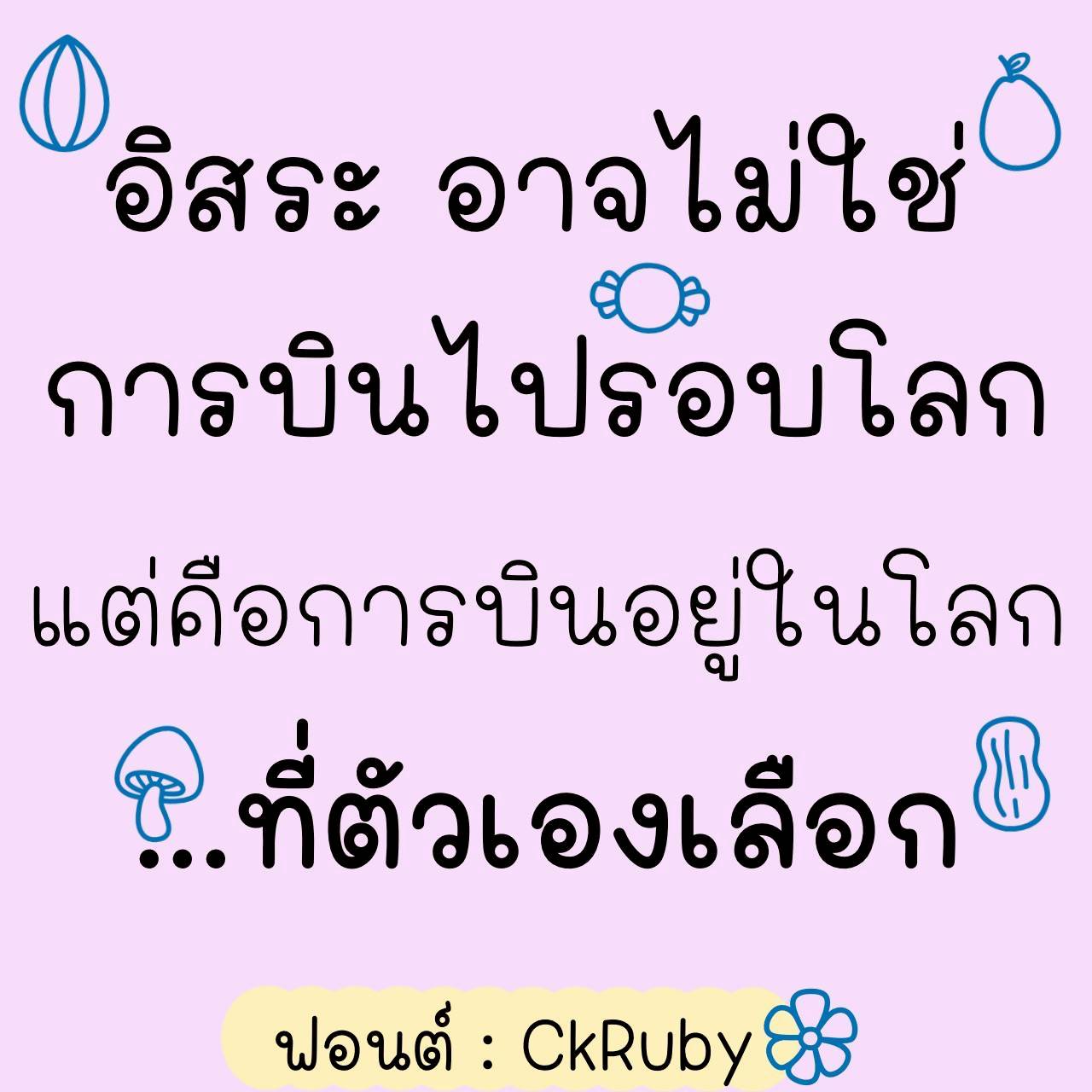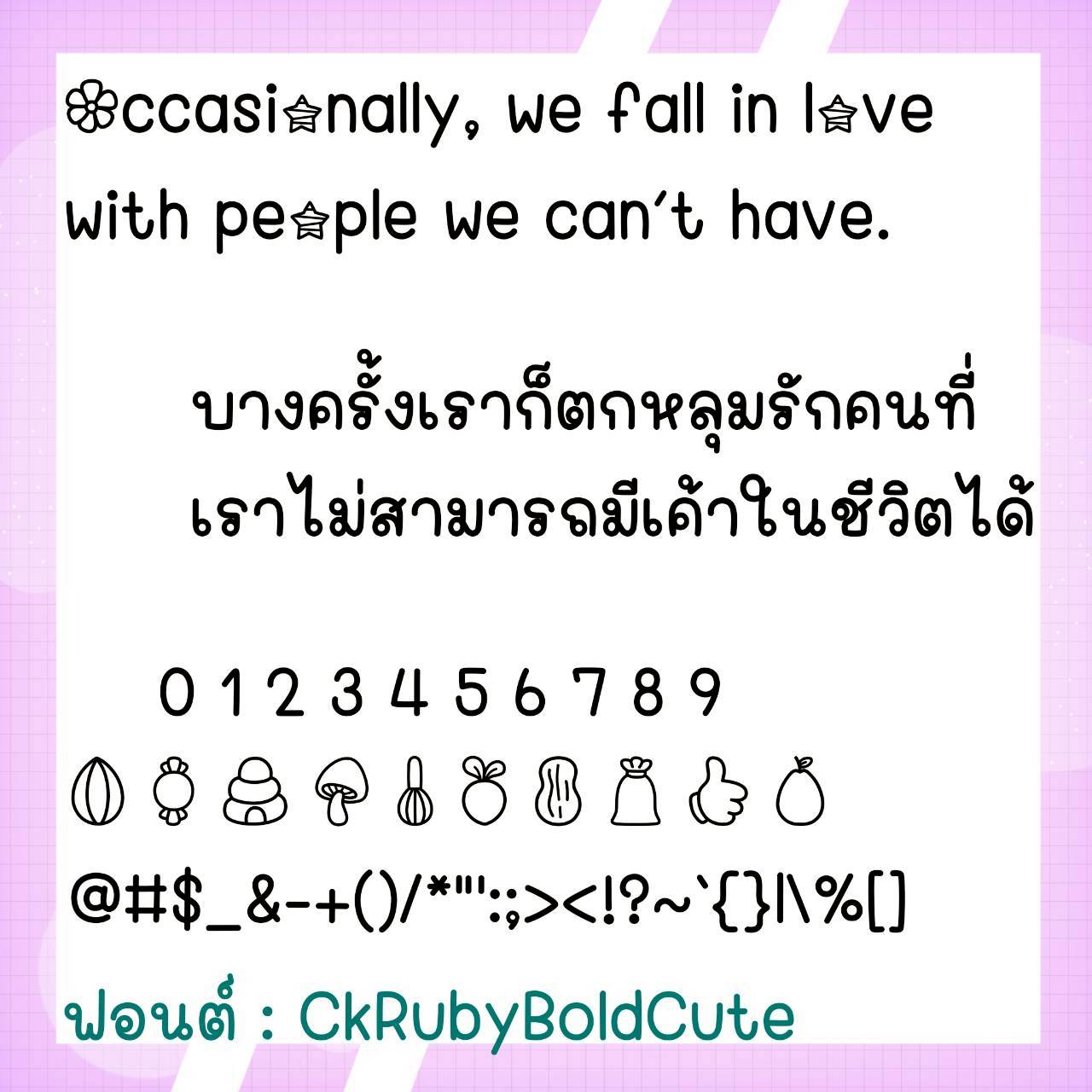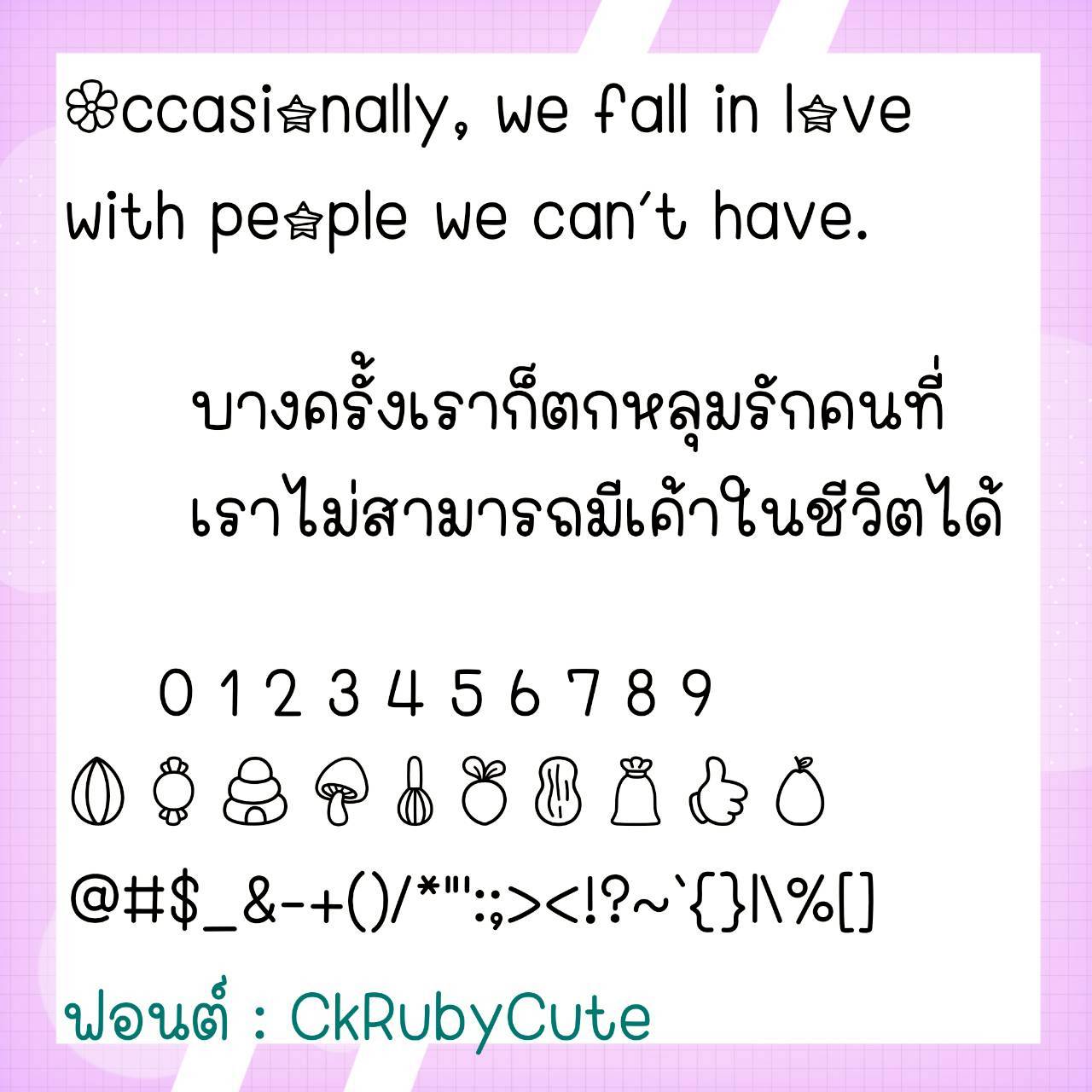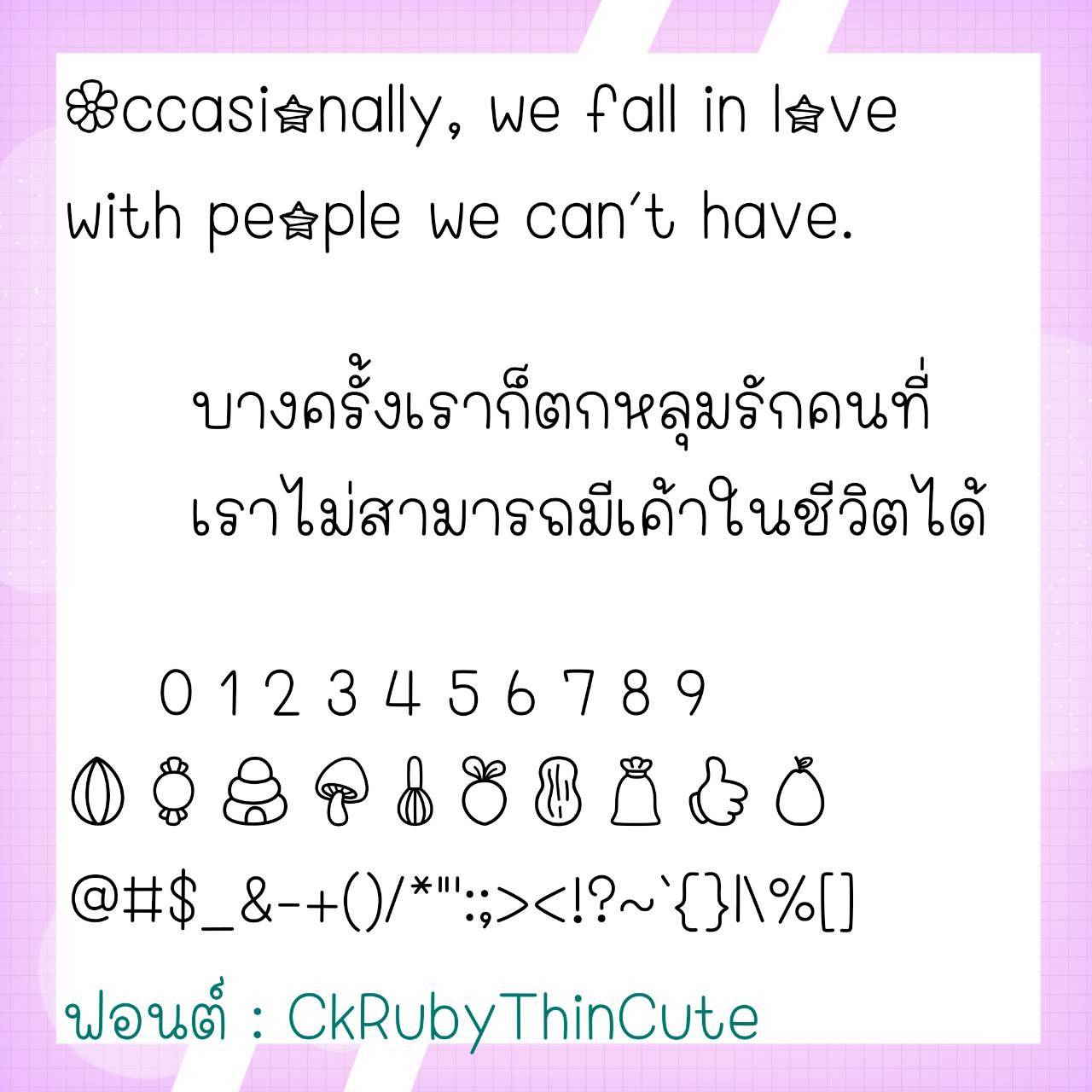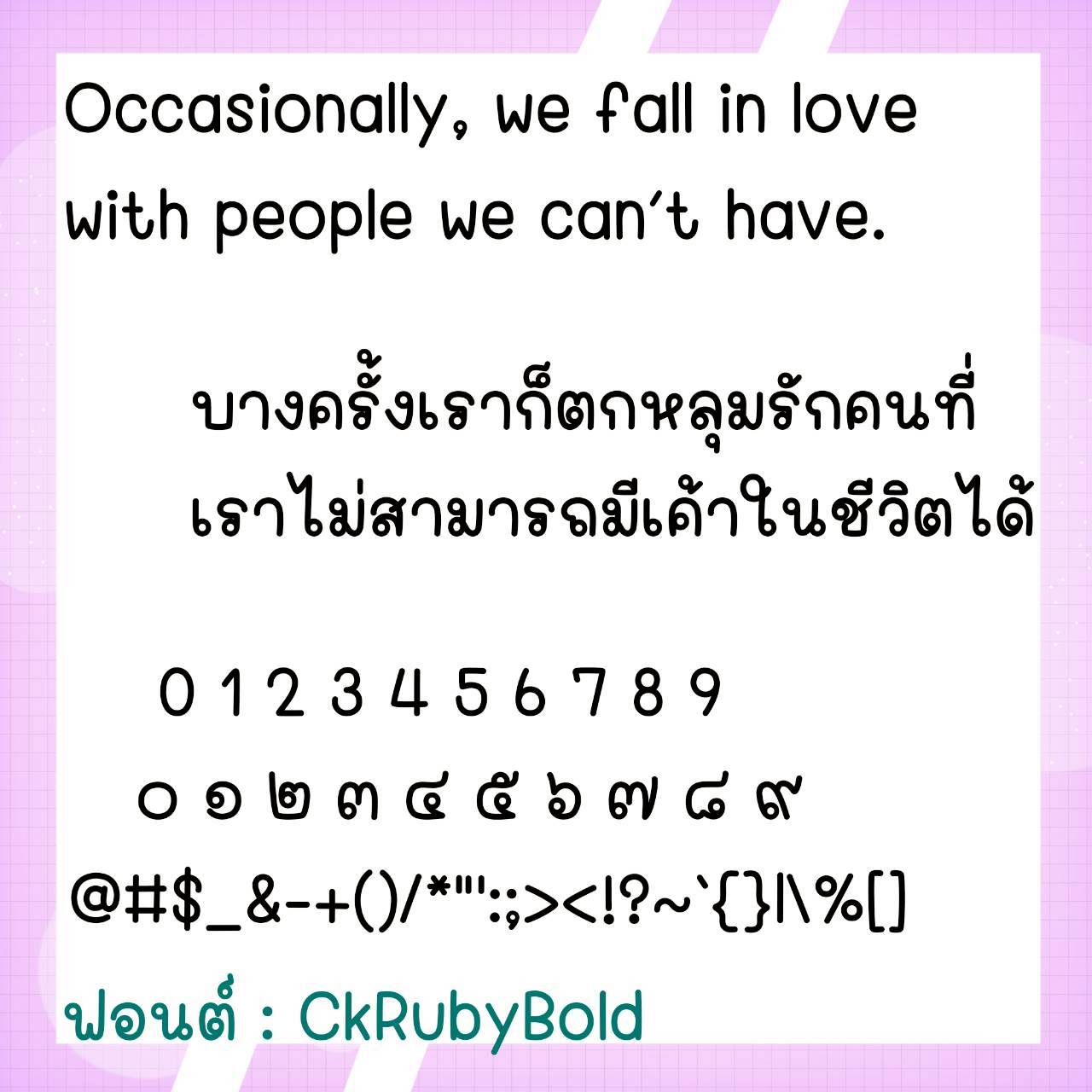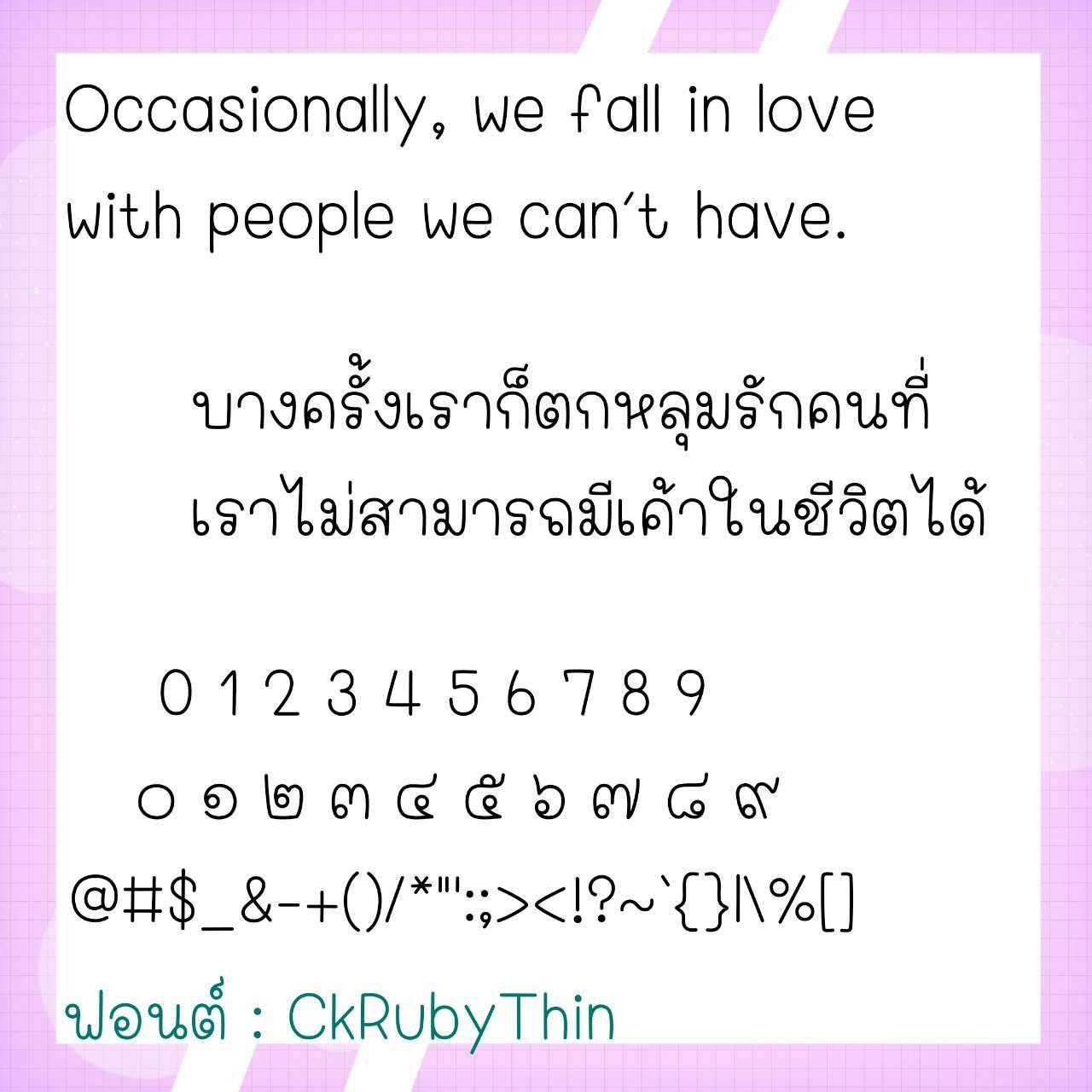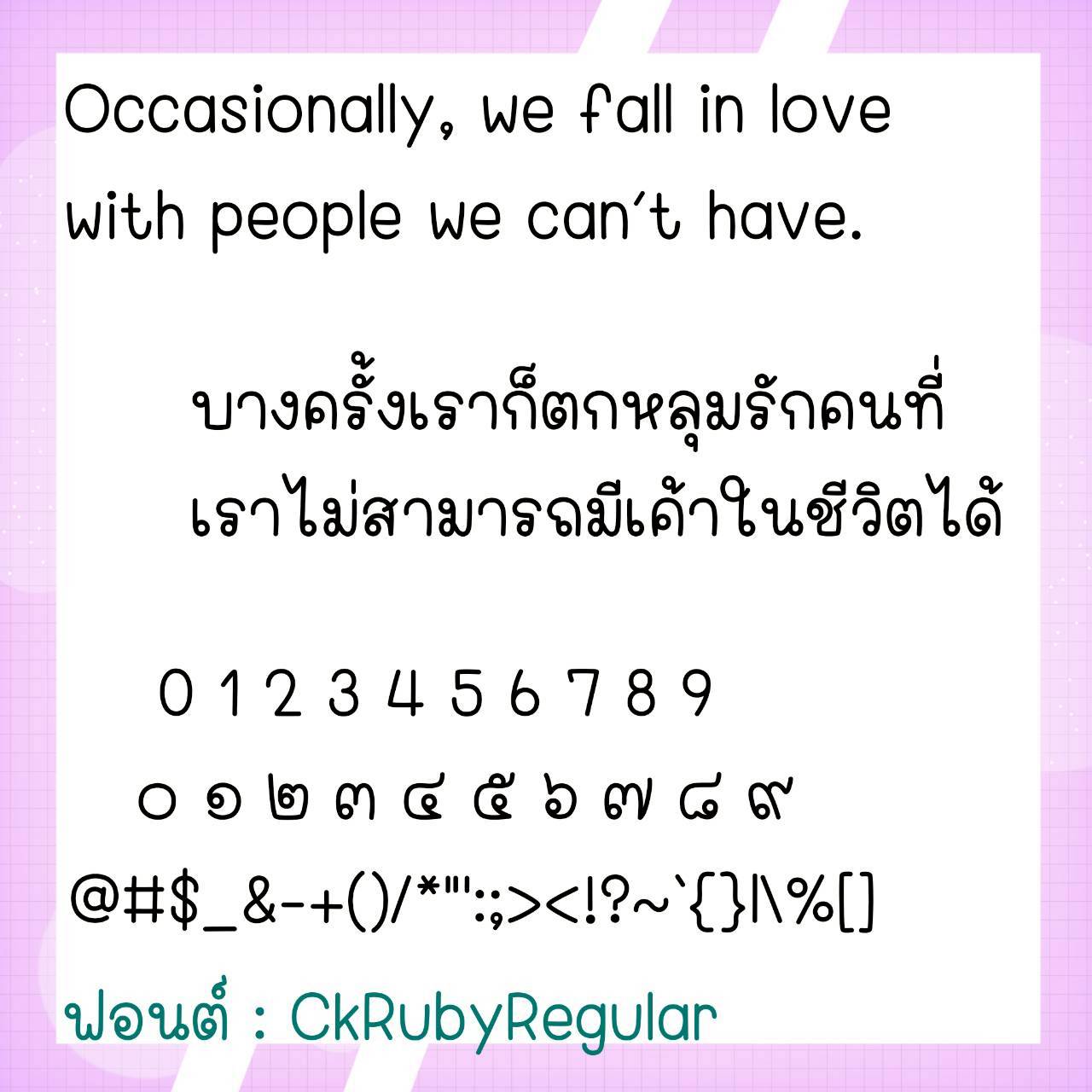
Font CkRuby
ชื่อสินค้า : Font CkRuby 💙
🔸 ฟอนต์ลายมือแนวตัวอ้วนกลม น่ารักอ่านง่ายสบายตา ดูมีความวัยรุ่น ดีต่อใจดีต่อสายตา และยังมีไฟล์อิโมจิน่ารักๆที่ใช้แทนเลขไทยให้ด้วยค่ะ 🥰💙
🔹 This handwritten font has a cute, chubby style, is easy to read and pleasing to the eye. It has a youthful vibe, is pleasing to the eye, and also includes cute emoji files that can be used to replace Thai numerals. 🥰💙